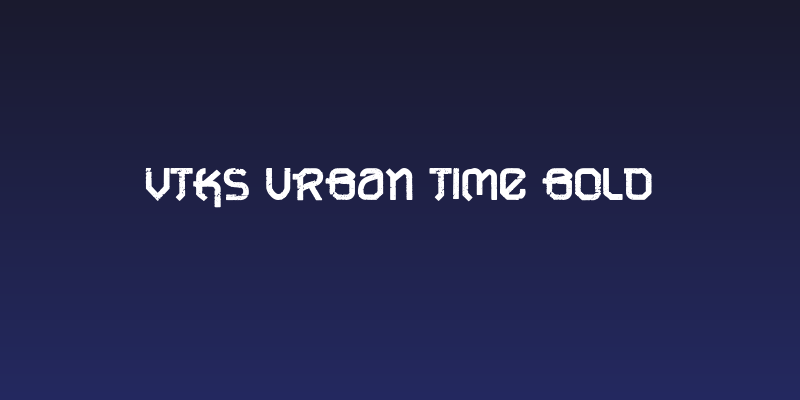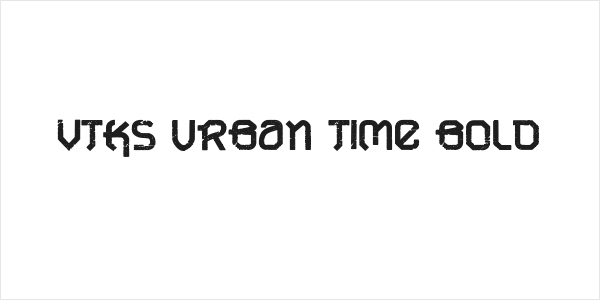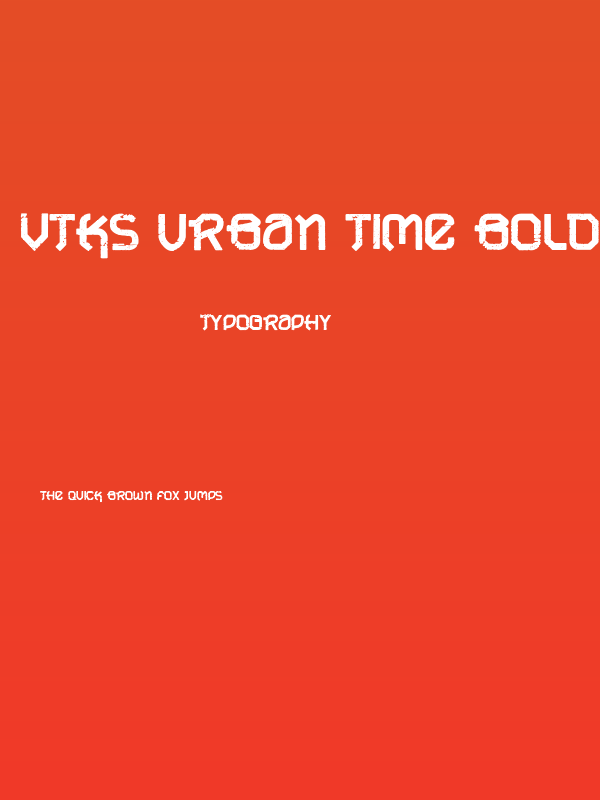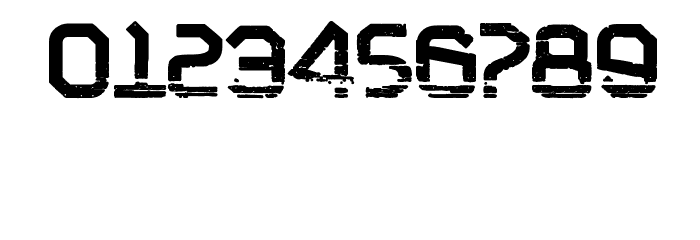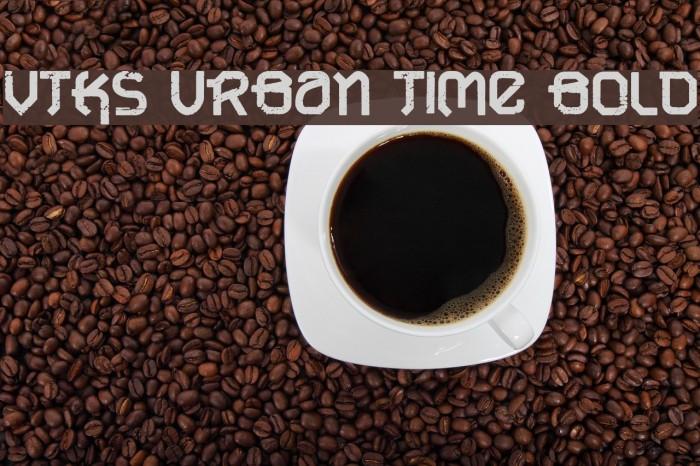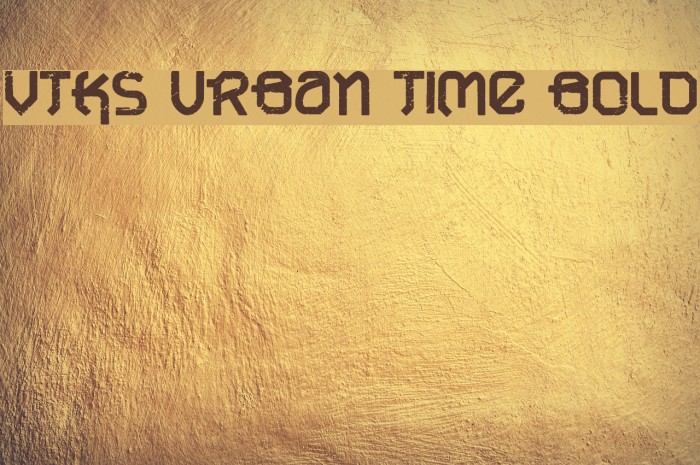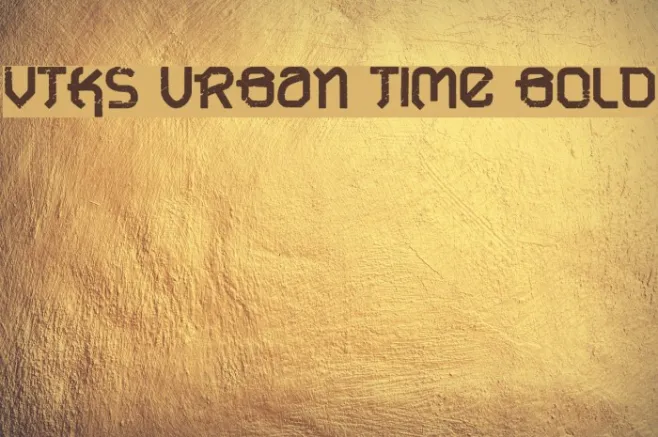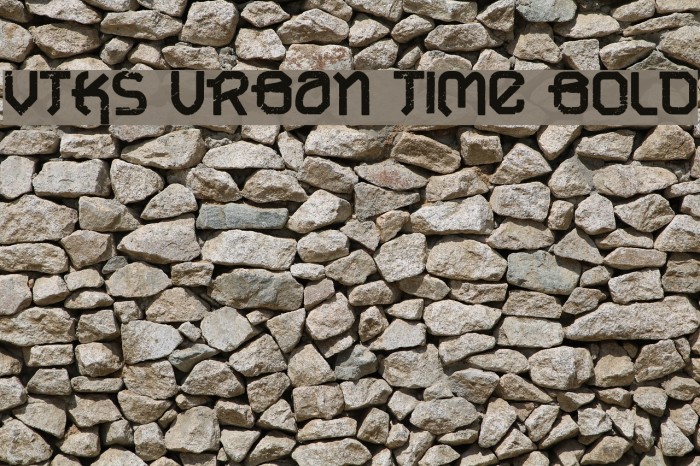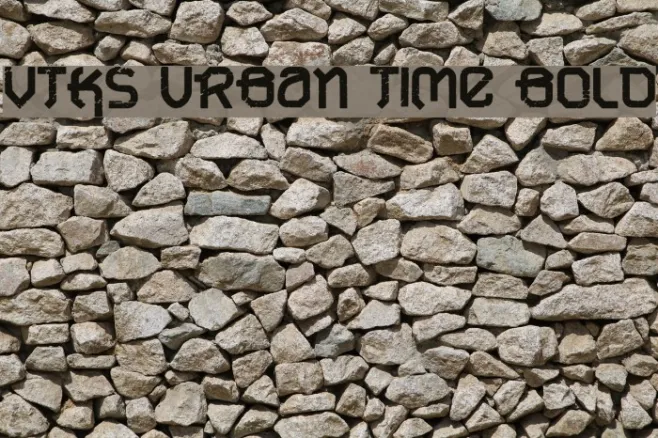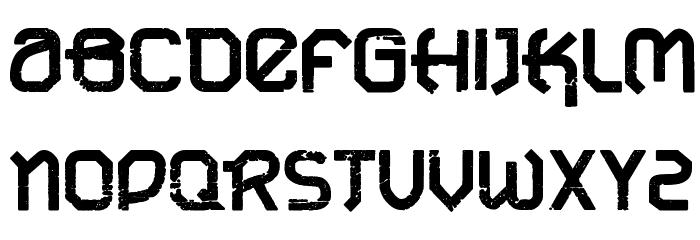
VTKS URBAN TIME bold Font
| Stile generale | Modern, Urban, Edgy |
| Progetti proposti | Ideal for street art designs, urban-themed posters, album covers, and edgy branding projects. |